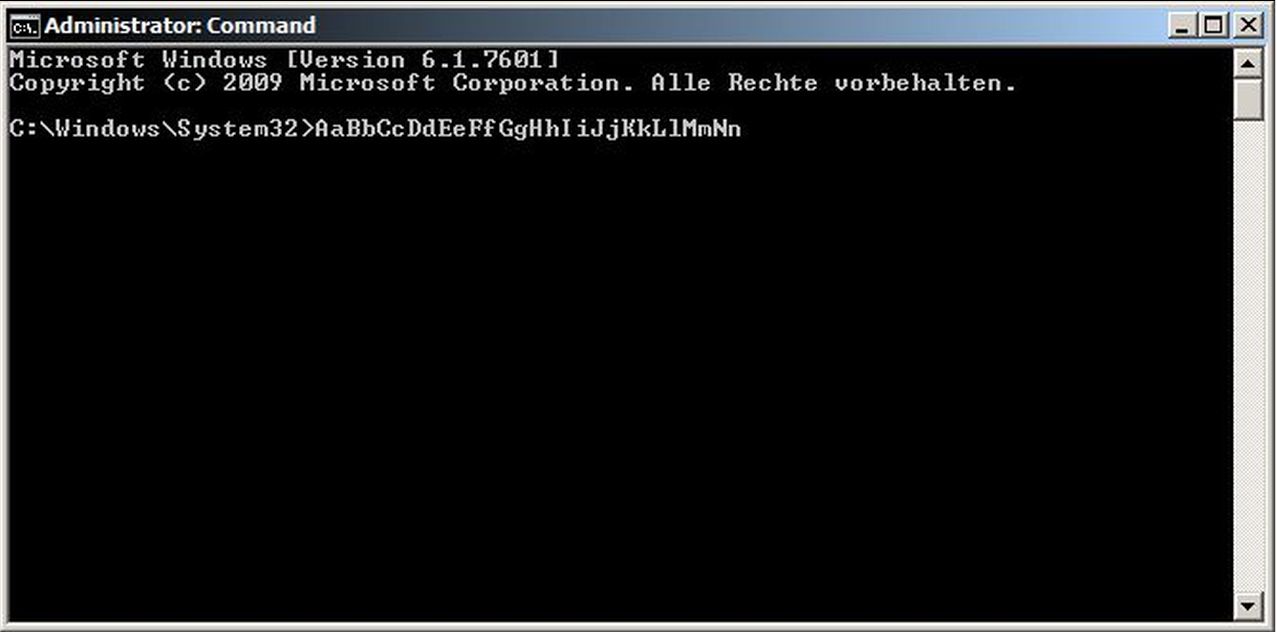
Schriftart in der Eingabeaufforderung / Konsole
Altes Thema, aber nach stundenlanger Recherche hab ich immer noch keine Antwort. Welche Schriftart wird verwendet, wenn man die Eingabeaufforderung mit Standard-Einstellungen öffnet, also Rasterschriftart 8x12? "Fixedsys" kann es kaum sein, denn Fixedsys hat keine Serifen, wie sie im Konsolenfenster deutlich bei B, D, E, F, q oder z zu sehen sind.
Außerdem: Wie kann es sein, daß mir verschiedene Programme verschiedene installierte Schriftarten anzeigen? DP4 etwa "verschweigt" die Schriftarten System und Terminal (die auch in Word nicht zu finden sind), obwohl beide im Fonts-Ordner sind. Der Fontviewer AMP zeigt absolut alles an. Wie das?
Edit: Ach hast du ja auch schon herausgefunden...
Wenn Du ein Cmd öffnest, kannst du oben die Titelleiste rechtsklicken und "Eigenschaften" wählen. Hier sagt mein Windows 8 im Reiter "Schriftart", neben 8x12 und Rasterschriftart, ganz unten(!), dass er als Schriftart "Terminal" gewählt hat.
Die Schriftarten System und Terminal sind Rasterschriftarten - also kein Truetype oder Openfont. Solche alten Kamellen lassen diverse Programme gerne weg, da diese nur ein paar ausgewählte Schriftgrößen haben.